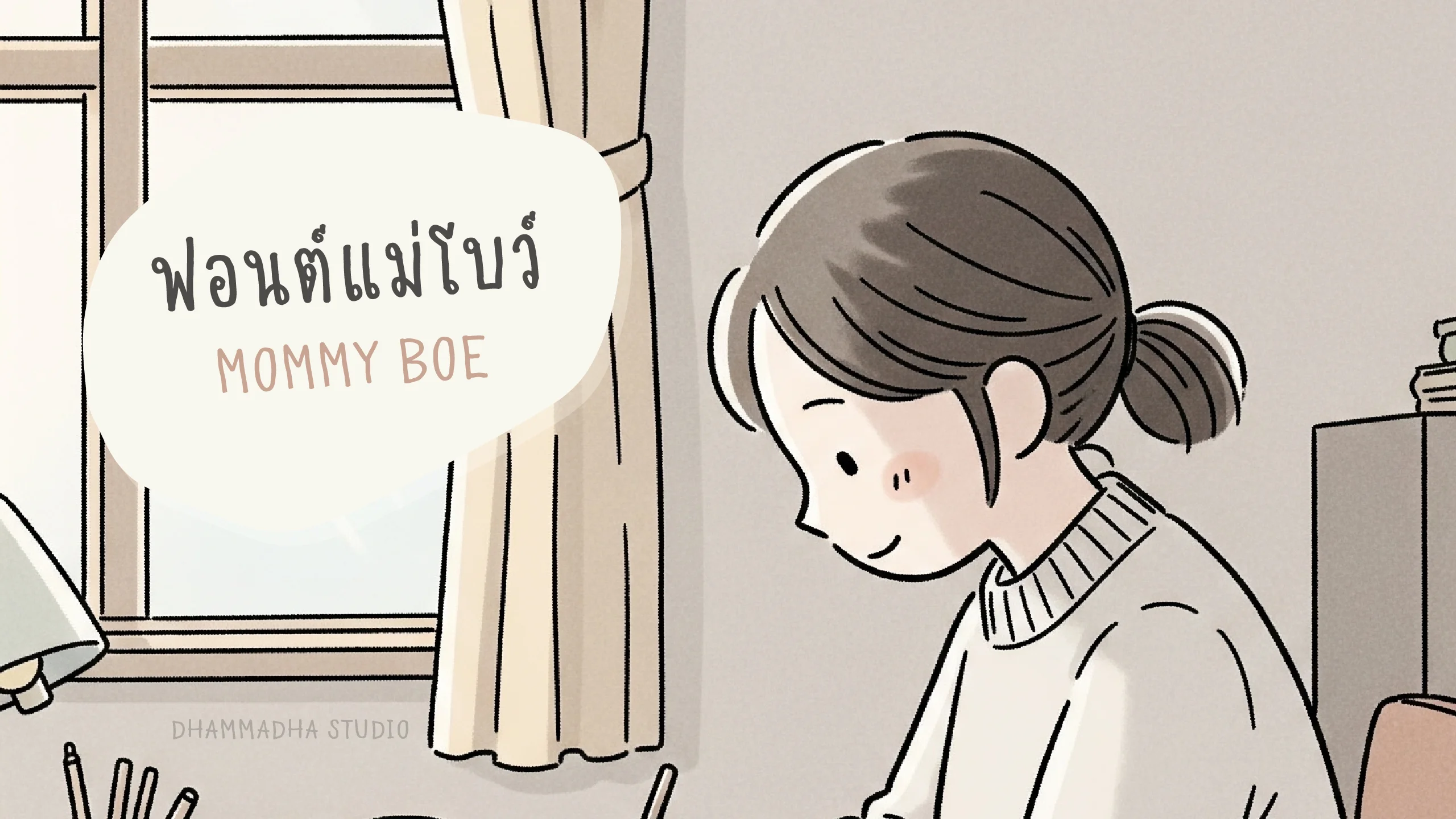
MOMMY BOE
ชุดอักษรลายมือที่สานต่อแรงบันดาลใจและความประทับใจจากฟอนต์ยอดนิยมอย่าง "เด็กชายโปเต้" โดยในครั้งนี้เราถ่ายทอดท่วงทำนองของลายเส้นผ่านปลายปากกาของคุณแม่โบว์ เพื่อส่งต่อความรัก ความอาทร และความอบอุ่นที่ถักทออยู่ในทุกตัวอักษร มอบบรรยากาศที่ดูนุ่มนวล เรียบง่าย แต่เปี่ยมไปด้วยความจริงใจที่พร้อมจะโอบอุ้มทุกข้อความของคุณให้ดูพิเศษและมีความหมายยิ่งขึ้น ด้วยบุคลิกที่ดูใจดีและเป็นธรรมชาติ "แม่โบว์ | MOMMY BOE" จึงเป็นตัวเลือกที่สมบูรณ์แบบสำหรับงานออกแบบที่ต้องการสื่อสารถึงความรักและความใส่ใจ ไม่ว่าจะเป็นคอนเทนต์เกี่ยวกับครอบครัว การสร้างแบรนด์สินค้าสำหรับแม่และเด็ก งานกราฟิกที่เน้นความละมุน หรือแม้แต่จดหมายขอบคุณที่ต้องการความรู้สึกเป็นส่วนตัว ฟอนต์ชุดนี้จะช่วยเติมเต็มความรู้สึกดีๆ และทำให้ทุกการสื่อสารของคุณดูอบอุ่น อ่อนโยน และเข้าถึงหัวใจของผู้อ่านได้อย่างลึกซึ้ง ออกแบบโดย : Menee Khong-Udnun พัฒนาฟอนต์โดย : Montonn Thanaroj